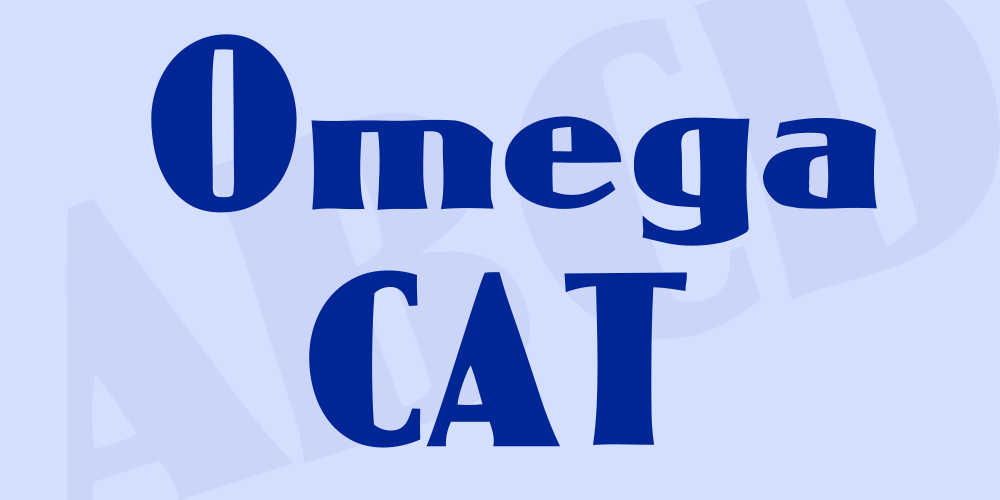
A fonte Omega CAT foi criada pelo designer Peter Wiegel, oferecendo uma escolha atraente para projetistas que buscam um estilo serif elegante e sofisticado. Esta fonte cativante é perfeita para criar gráficos profissionais com um toque de sofisticação, sendo ideal para cabeçalhos e textos de destaque em websites ou impressões. Com seu design cuidadosamente elaborado por Hamilton, Omega CAT oferece uma variedade impressionante de opções visuais. Seu estilo elegante é atraente tanto para o design web quanto para materiais impressos, criando um impacto imediato e memorável. A fonte mantém sua natureza legível graças ao seu traçado regular e bem definido, que facilita a leitura mesmo em grandes tamanhos. É uma escolha inteligente tanto para aplicativos profissionais quanto para ambientes de design pessoal que valorizam elegância e sofisticação. Com essa fonte no seu arsenal, você terá um recurso poderoso para personalizar qualquer projeto gráfico com o toque perfeito de sofisticação. Para mais informações ou download da fonte, visite o site do designer: http://www.peter-wiegel.de.